지난번 글에서 상업적 이용 가능한 무료 폰트 중 고딕 종류의 폰트들 중 추천드릴만한 것들에 대해 한번 정리를 했었습니다. 이번에는 그 2번째 시간. 명조편입니다. 사실 우리가 흔히 명조체라고 부르는 이 단어는 명나라 왕조라는 뜻을 가진다고 합니다. 명나라 활자체를 활용하여 개발한 글자꼴이라는 의미로 명조체라고 부르기 시작했다고 합니다. 명조체 고딕체와 달리 전통적인 느낌이나 고급스러운 분위기를 낼 수 있는 폰트입니다. 고딕체와 마찬가지로 상업적 이용이 가능한 무료 명조체를 7개 추천해드리려고 합니다.
상업적 이용 가능한 무료폰트 명조 폰트 7개
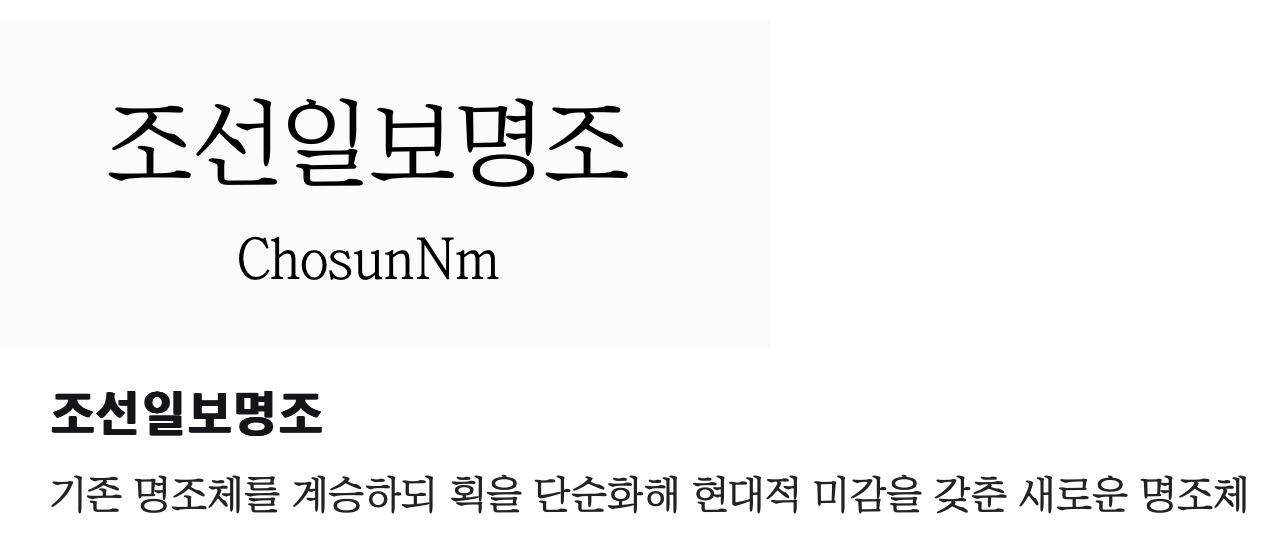
1. 조선일보명조
조선일보명조는 조선일보에서 제공하는 명조체 폰트입니다. 깔끔하고 단정한 글자 형태가 특징. 주로 신문 기사나 문서 작성에서 많이 사용되며, 전통적인 명조체의 정갈함을 잘 살린 디자인입니다. 글자 구조가 안정적이기 때문에 본문용 폰트로 많이 사용되고 있으며, 긴 글을 읽을 때도 눈에 피로감이 덜하다는 장점이 있습니다.
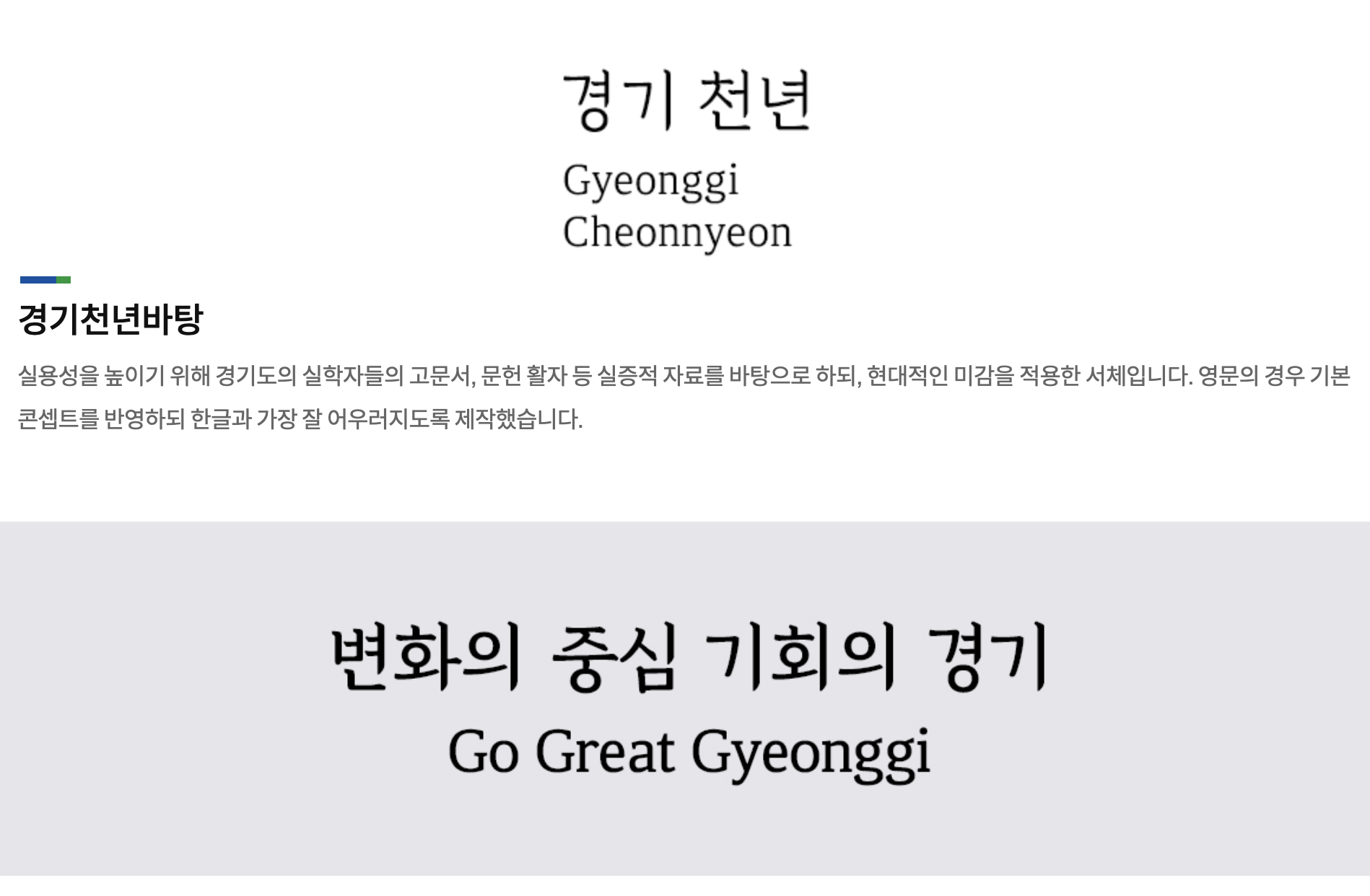
2. 경기천년바탕
경기천년바탕은 경기도에서 제공하는 무료 폰트입니다. 전통적인 명조체의 느낌을 현대적으로 재해석한 디자인. 부드러운 곡선과 단단한 직선이 조화를 이루어 고전적이면서도 세련된 느낌을 줍니다. 가독성이 좋아 본문과 제목 모두에서 활용하기 좋습니다.
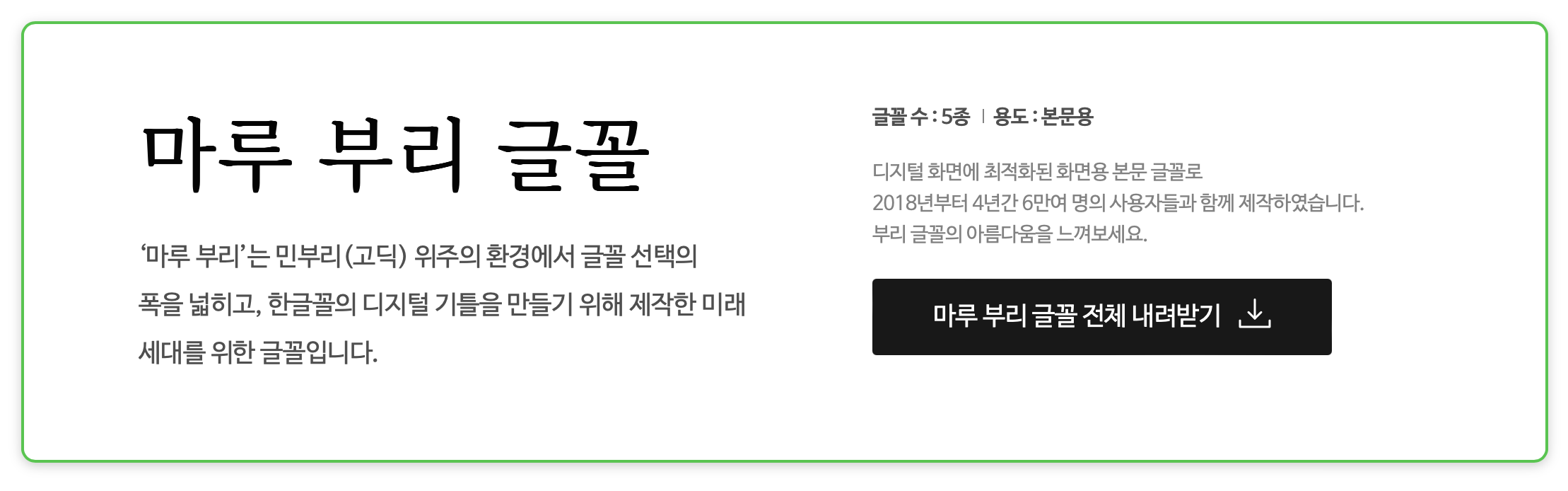
3. 마루부리
마루부리는 네이버에서 제공하는 명조체 폰트입니다. 한국 전통 서체의 느낌을 현대적인 감각으로 재해석한 디자인입니다. 글자 간의 여백이 넉넉하고, 부드러운 곡선이 많아 따뜻하고 편안한 느낌을 줍니다.
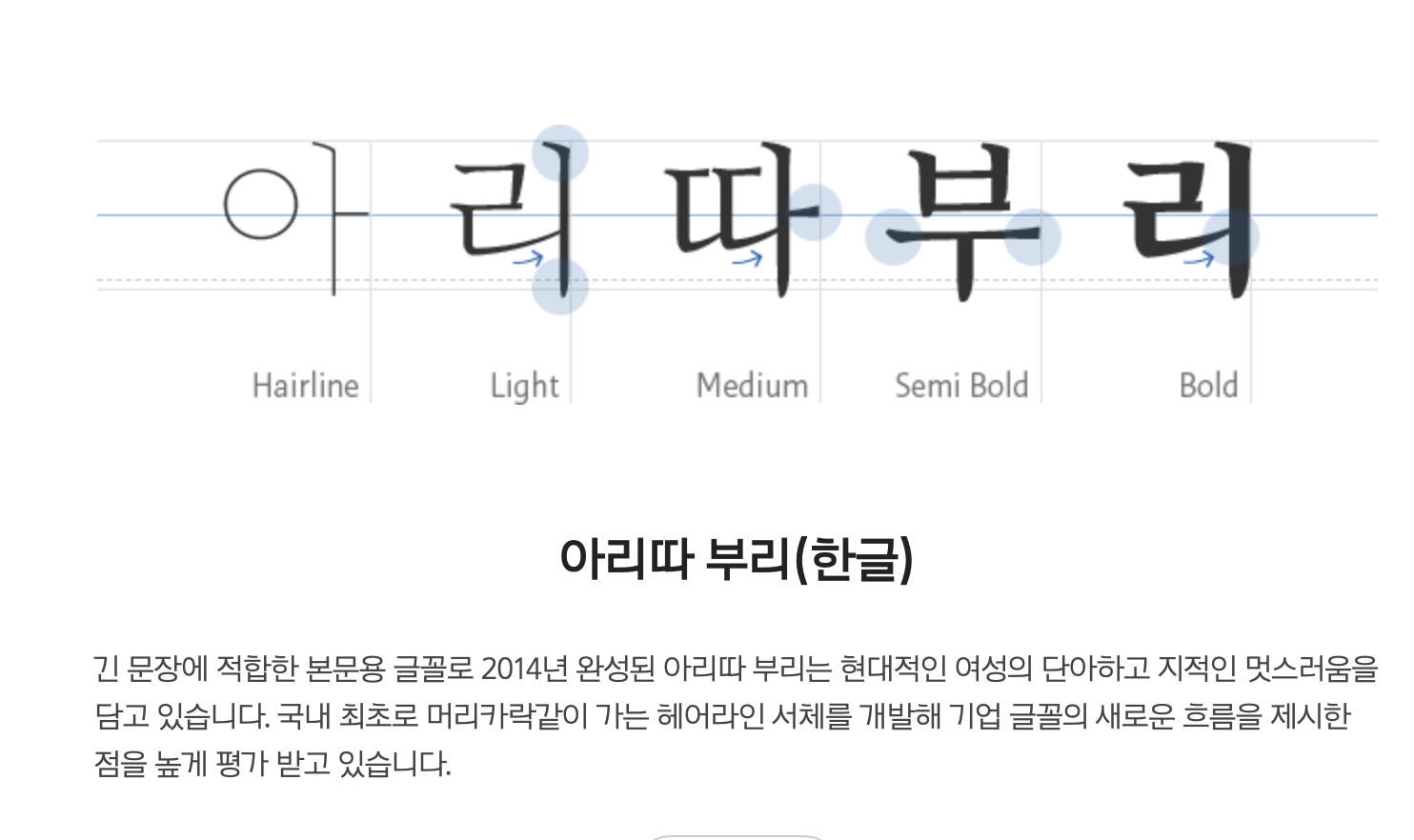
4. 아리따부리
아리따부리는 아모레퍼시픽에서 제공하는 명조체 폰트입니다. 단정하고 세련된 디자인이 특징. 고급스럽고 여성스러운 느낌을 주어 뷰티 관련 디자인에서 자주 사용된다고 합니다. 정형화된 명조체의 틀을 벗어나 부드럽고 감성적인 분위기를 연출할 수 있어 다양한 용도로 활용 가능합니다.
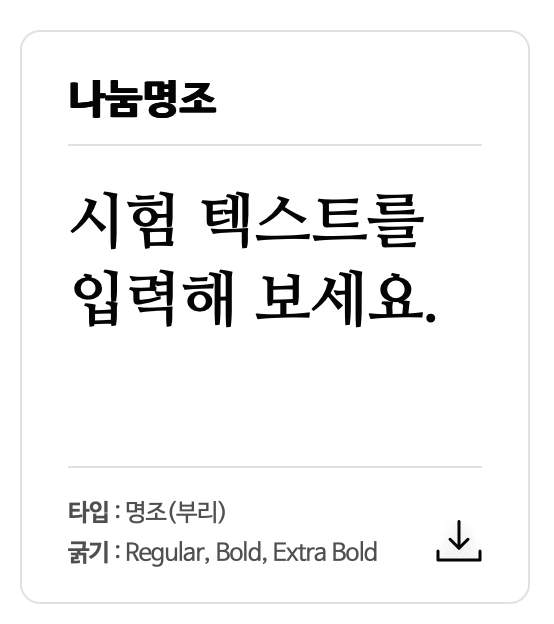
5. 나눔명조
나눔명조는 네이버에서 제공하는 대표적인 명조체 폰트입니다. 안정적인 글자 구조와 높은 가독성이 특징. 다양한 굵기를 제공하여 본문용, 제목용으로 모두 활용할 수 있습니다. 깔끔하고 단정한 명조체의 정석 폰트입니다.
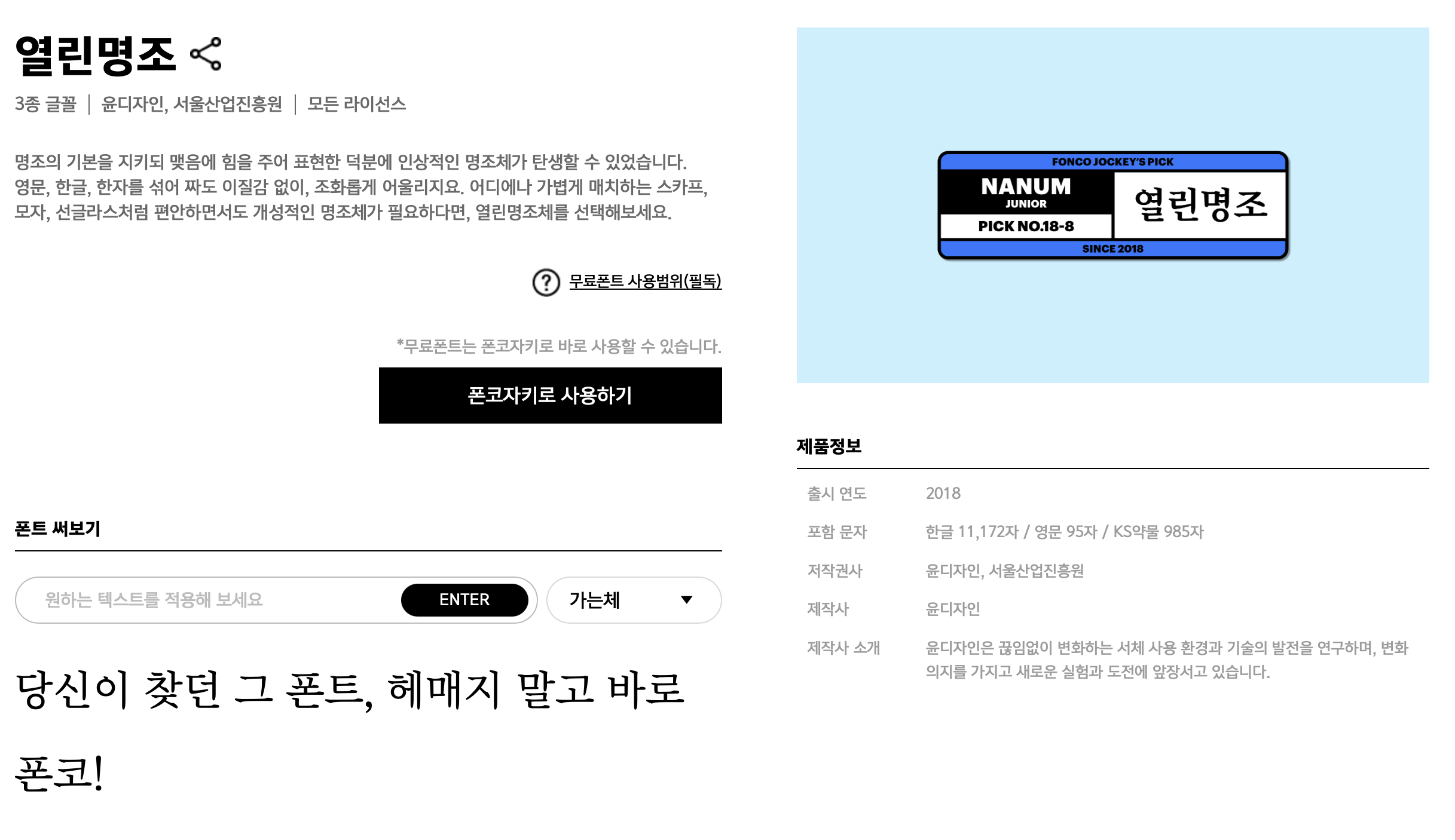
6. 열린명조
열린명조는 서울특별시교육청에서 제공하는 무료 폰트입니다. 전통적인 명조체의 아름다움을 유지하면서도 현대적인 요소를 가미한 디자인. 글자 간의 여백이 넉넉해 가독성이 좋습니다.
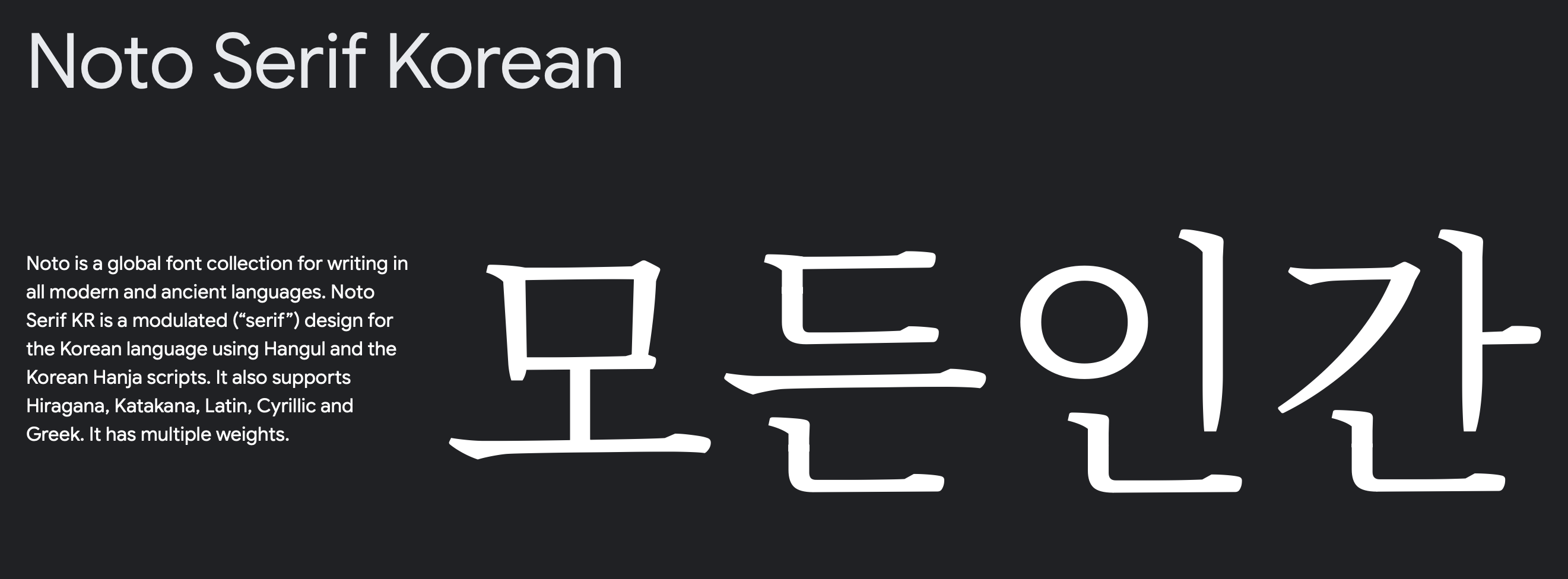
7. 본명조 (Noto Serif KR)
본명조(Noto Serif KR)는 본고딕(Noto Sans KR)과 마찬가지로 구글과 어도비가 공동으로 개발한 글로벌 폰트입니다. 다양한 언어를 일관된 스타일로 표현할 수 있습니다. 전통적인 명조체의 미를 살리면서도 현대적인 감각을 더해 깔끔하고 세련된 느낌을 줍니다.